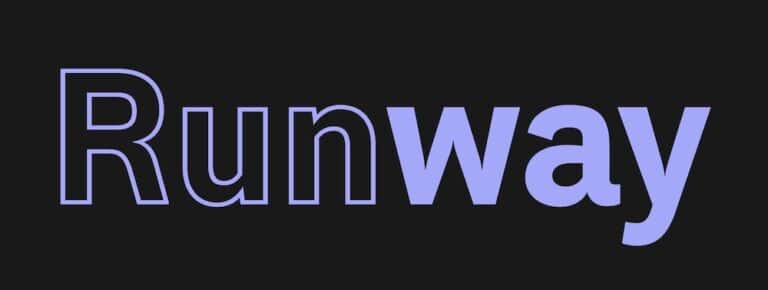
Era Grotesk: Neue Schrift aus Finnland
Von der finnischen Foundry Typolar kommt die Schriftfamilie Era in einer normalen und einer Outline-Version.
Inspiriert ist die Serifenlose von Industrieschriften aus dem 19. Jahrhundert, die wiederum den Weg für einige der berühmtesten Schriften der Typografiegeschichte ebneten, beispielsweise Bertholds Akzidenz-Grotesk oder Neue Haas Grotesk. Obwohl diese Typen für uns eng mit dem Neo-Grotesk-Stil verknüpft sind, reichen dessen Ursprünge noch weiter zurück. Nämlich bis ins späte 18. Jahrhundert, als flexible Stifte anfingen, das handschriftliche Schreiben zu dominieren. Es dauerte eine Weile, bis sich dieser Stil auch in Schriften für den Druck wiederfand, aber schließlich hielten serifenlose Buchstabenformen Einzug in die alltägliche Typografie.
Auf diesen Spuren wandert Era Grotesk, gestaltet von Typolar-Gründer Jarno Lukkarila. Er legte die Familie in 16 Schnitten an, acht Stärken von Hairline bis Heavy plus Italics. Zu der normalen Variante zeichnete Jarno Lukkarila außerdem eine Outline-Version. die komplette Familie kostet knapp 400 Euro und ist über Typolar zu beziehen.